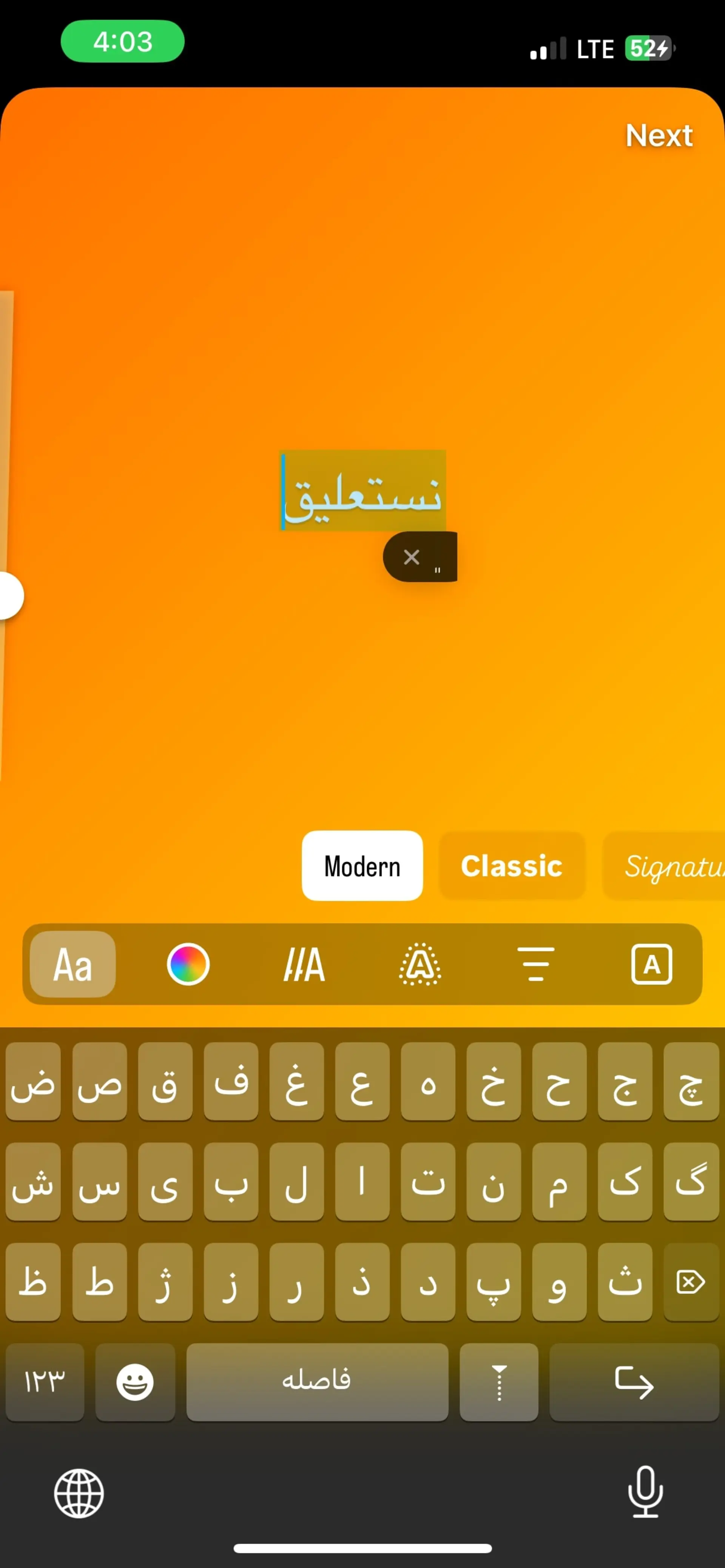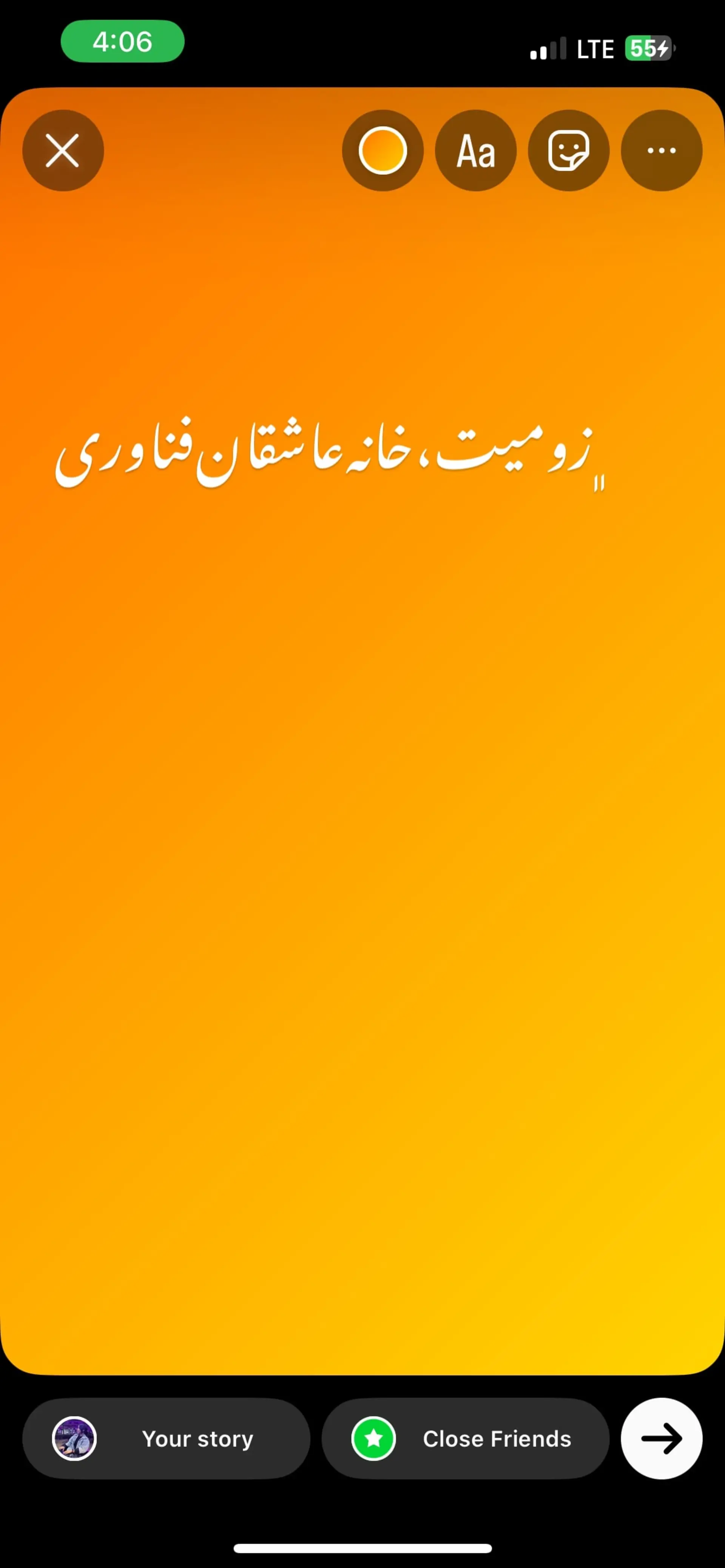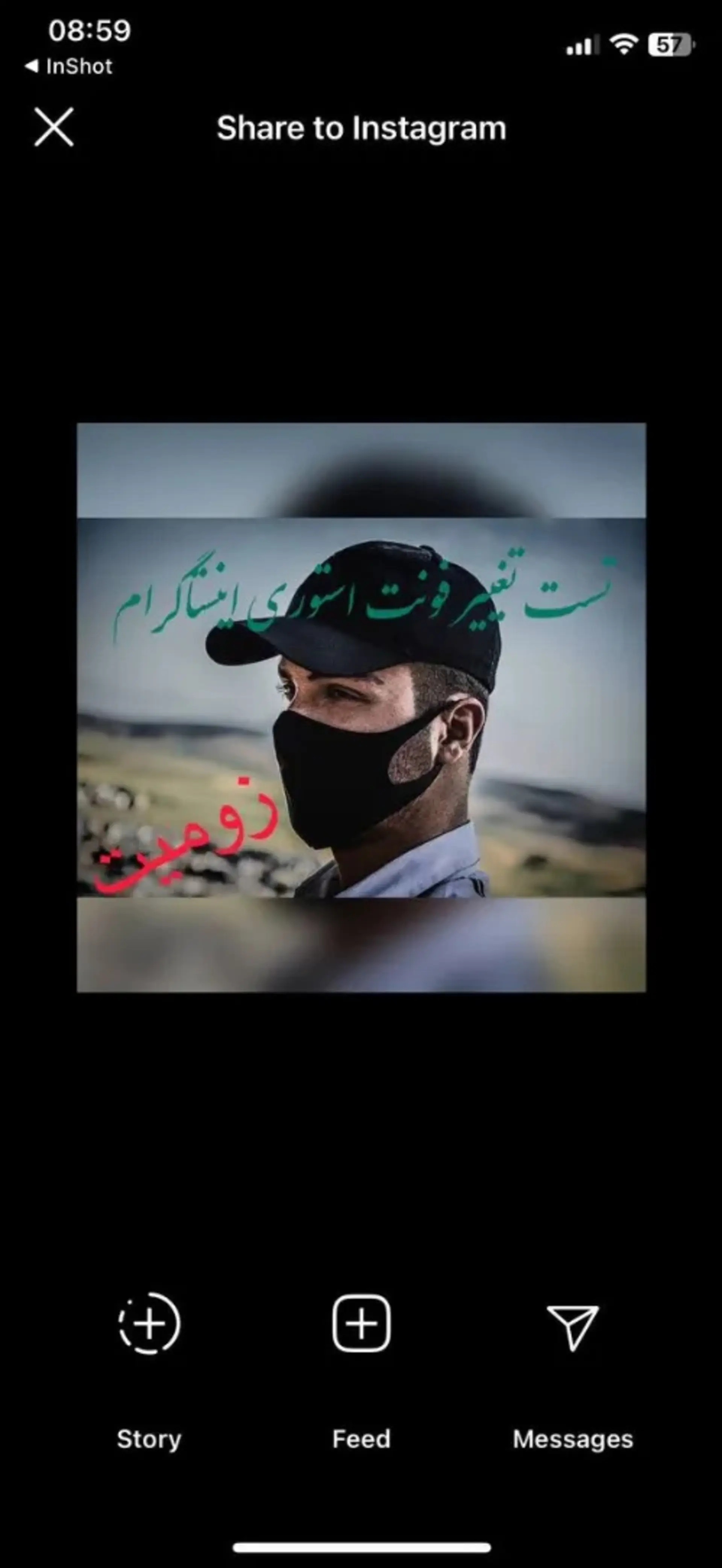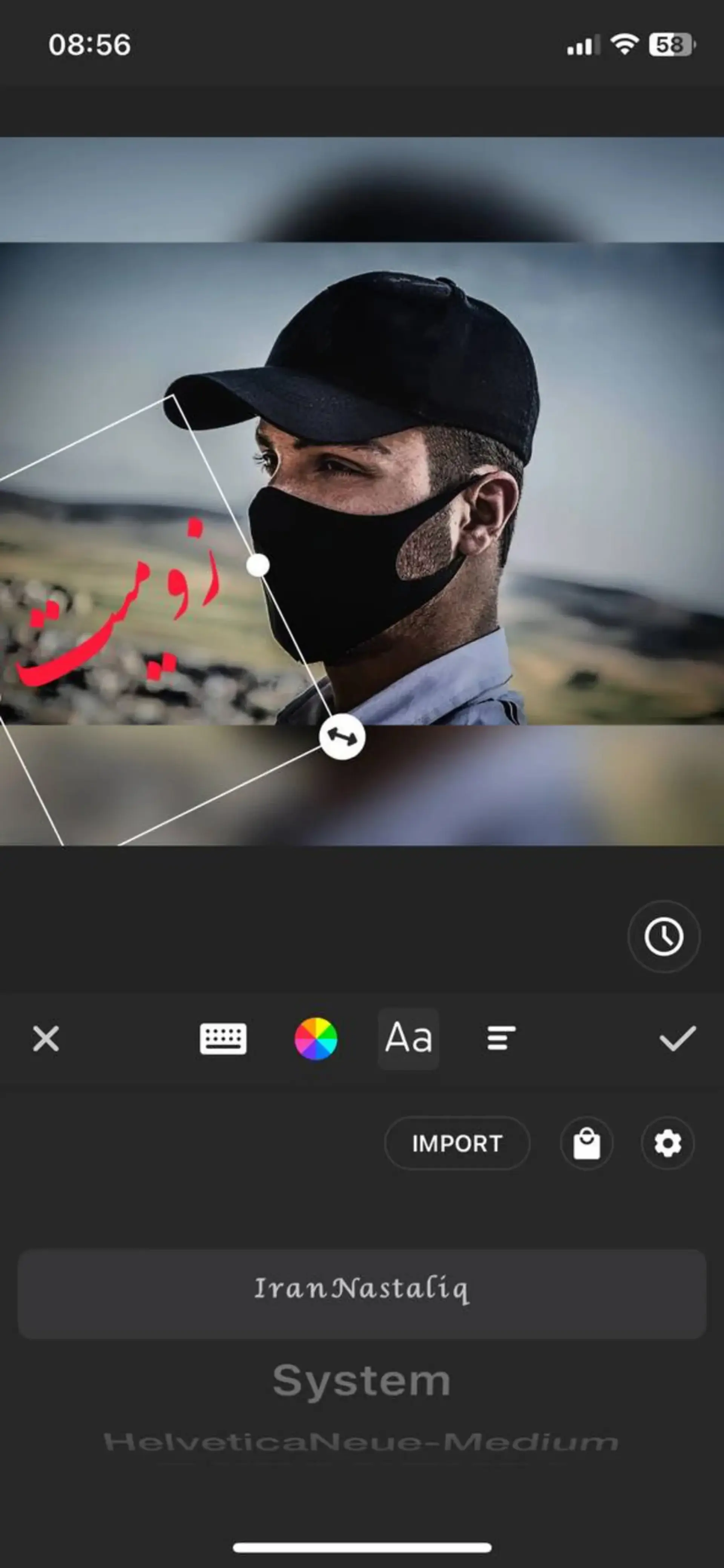
راهنمای کامل تغییر فونت اینستاگرام؛ صفحه اینستاگرامتان را به یادماندنی کنید
تغییر فونت اینستاگرام راهی خلاقانه برای شخصیسازی پروفایل است که به شما امکان میدهد تا با فونتهای خاص، پستها و بیو خود را جذابتر کنید.
آیا تابهحال به این موضوع فکر کردهاید که چرا برخی از پروفایلهای اینستاگرام بیشتر از بقیه به چشم میآیند؟ یکی از رازهای جذابیت پروفایل، استفاده از فونتهای خاص و خلاقانه است. فونتها نهتنها میتوانند استایل شخصی شما را منعکس کنند، بلکه به پیج شما هویت و جذابیتی متفاوت میبخشند.
کاربران اینستاگرام همیشه بهدنبال روشهایی برای شخصیسازی و بهبود تجربه کاربری خود هستند؛ از سؤالهای سادهای مثل چگونه بفهمیم چه کسانی ما را فالو کردند تا تغییر ظاهر پروفایل با تغییر فونت. در این مقاله، به روشهای سادهای برای تغییر فونت اینستاگرام میپردازیم که به شما کمک میکنند تا پروفایلتان را جذابتر کنید.
نکات مهم برای تغییر فونت اینستاگرام
تغییر فونت اینستاگرام به کاربران امکان میدهد تا نوشتههای خود را با استایلهای مختلفی نمایش دهند و ظاهری خاص و جذاب به پروفایل و پستهای خود ببخشند. یکی از گزینههای محبوب در بین کاربران، استفاده از فونت آیفون برای اینستاگرام است که بهدلیل ظاهر شیک و خوانا، طرفداران زیادی دارد. بسیاری از کاربران با انتخاب فونت آیفون برای اینستاگرام، صفحهی خود را شبیه به طراحی مینیمال و ظریف آیفون میکنند. استفاده از این فونت میتواند به پروفایل ظاهری متفاوت و مدرن ببخشد و حس خاص بودن را القا کند.
در استفاده از فونتهای متنوع در اینستاگرام، به نکات زیر توجه کنید:
- تعادل: از تعداد کمی فونت استفاده کنید تا محتوا شلوغ و نامنظم نشود.
- سازگاری با برند: فونتهایی را انتخاب کنید که با هویت و شخصیت برندتان همخوانی داشته باشند.
- خوانایی: مطمئن شوید فونتها خوانا هستند و مخاطب میتواند بهراحتی متن شما را بخواند.
- هماهنگی با محتوا: فونت را براساس نوع پیام و احساسات مورد نظر انتخاب کنید؛ مثلاً فونتهای دستنویس برای صمیمیت، یا بولد برای تأکید انتخابهای بهتری هستند.
- ثبات: برای ایجاد هویت بصری ماندگار، بهتر است برخی فونتهای اصلی را در پستهای مختلف ثابت نگه دارید.
آموزش تغییر فونت اینستاگرام
با روشهای مختلفی مانند استفاده از سایتها و اپلیکیشنهای جانبی، امکان تغییر فونت بیو، کپشن و استوریها فراهم میشود. در ادامه به بررسی ابزارهای ساده و کاربردی برای تغییر فونت اینستاگرام میپردازیم تا صفحهای حرفهای و منحصربهفرد داشته باشید.
تغییر فونت استوری اینستاگرام
با استفاده از گزینههای پیشفرض اینستاگرام یا ابزارهای جانبی، میتوانید فونتهای متنوع و خاصی را در استوریهای خود بهکار ببرید و استایل منحصربهفردی ایجاد کنید. برای تغییر فونت استوری اینستاگرام مراحل زیر را دنبال کنید:
- پس از واردشدن به بخش استوری، عکس یا ویدیوی مورد نظرتان را انتخاب کنید.
- گزینهی «Aa» را انتخاب و متن مورد نظرتان را وارد کنید.
- از میان فونتهای پیشفرضی که اینستاگرام در پایین صفحه پیشنهاد میدهد، گزینههای مختلف را امتحان کنید تا به فونت استوری دلخواهتان برسید.
اینستاگرام علاوهبر فونتهای مختلف در استوری، امکان تغییر رنگ، اندازه و موقعیت متن را هم برای کاربران خود فراهم کرده است. شما حتی میتوانید پس از نوشتن متن مورد نظرتان، از گزینههای راستچین، چپچین یا وسطچین هم برای متفاوتکردن استوری خود استفاده کنید.
هنگام کار با استوری اینستاگرام، علاوهبر قابلیتهایی مثل تغییر فونت استوری برای جذابتر کردن محتوا، ممکن است با چالشهایی مثل حذف ناخواستهی استوریها هم مواجه شوید. در این مواقع، اگر بدانید که چگونه استوری پاک شده را برگردانیم بهراحتی میتوانید استوریهای از دست رفته را بازیابی کنید. به این ترتیب، ضمن داشتن استوریهای جذابتر با فونتهای متنوع، از امنیت و حفظ محتواهای خود هم مطمئن خواهید بود.
تغییر فونت بیو اینستاگرام
تغییر فونت بیو اینستاگرام فرصتی است تا اولین نگاه مخاطب را خیره کنید و جلوهای خاص و متفاوت به پروفایل خود ببخشید. با انتخاب فونتهای جذاب و منحصربهفرد، میتوانید کنجکاوی بازدیدکنندگان را برای دنبالکردن بیشتر تحریک کنید. برای این کار میتوانید از وبسایتهایی مانند Cool Symbol استفاده کنید. برای تغییر فونت استوری اینستاگرام با استفاده از سایت مذکور، مراحل زیر را دنبال کنید:
- وارد صفحهی اصلی سایت شوید و در منوی سمت راست روی گزینهی Font Generator کلیک کنید.
- در کادر بالای صفحه متن خود را وارد کنید و با اسکرولکردن به پایین صفحه، روی فونت دلخواهتان ضربه بزنید.
نکته:
این وبسایت از زبان فارسی پشتیبانی نمیکند و فقط برای متنهای انگلیسی میتوانید از آن استفاده کنید.
تغییر فونت بیو اینستاگرام با ابزار تاوبیو
تاوبیو (TawBio) یک ابزار آنلاین است که به شما اجازه میدهد تا فونتهای خاص و جذابی برای متنهای خود ایجاد کنید. با استفاده از این ابزار میتوانید بدون نیاز به برنامههای پیچیده، متنهای فارسی زیبا و متنوعی را برای بیو، استوریها یا پستها در اینستاگرام طراحی کنید.
به نظر شما، آیا تغییر فونت بیو اینستاگرام و استفاده از نستعلیق میتواند تعامل و جذابیت صفحهی اینستاگرام را بیشتر کند؟ شما کدام فونت را برای پروفایل خود انتخاب میکنید؟
اپلیکیشن اینشات یکی از بهترین ابزارهایی است که میتوانید برای تغییر فونت اینستاگرام خود از آن استفاده کنید.
بله؛ شما میتوانید با استفاده از اپلیکیشنهایی مانند Canva، InShot، Persian calligraphy و Ana Muhtarif Al Khat این کار را انجام دهید.